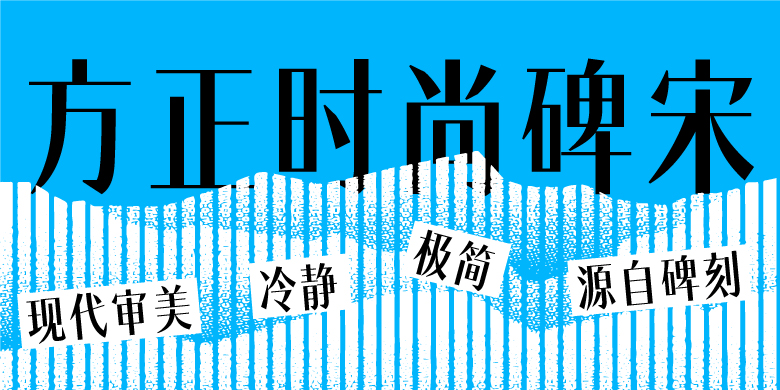
方正时尚碑宋家族
时尚碑宋获得GDC Award 2019 专业组 / 视觉传达类 / 文字设计 / 银奖。这是一款标题展示类字体,可用于但不限于时尚、艺术、极简产品、性冷淡风格等场景。笔形源自魏碑《龙门二十品》与现代宋体审美的结合,特别在撇捺曲线末端和勾点的微微斜切造形上,既抽象了铭刻的痕迹,又在功能上避免了飘尖,让笔形既钝又峭,且某些交叉处自然收缩而优化了显示,在几何构成与书法结体、功能与形式上自然融合,顺应当今屏幕显示与印刷工艺的高清晰还原,呈现一种极冷静、极锐利、极简洁的文字雕刻之美。